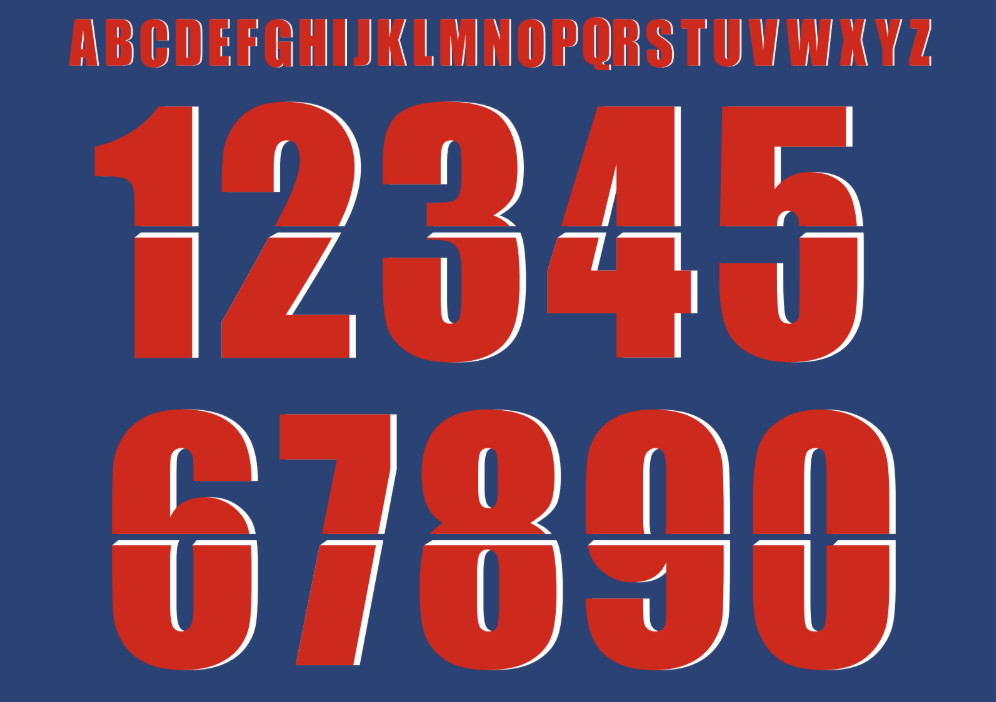
O Paris Saint-Germain nunca entra em campo apenas para jogar; o clube entra para desfilar estilo. Com a chegada do novo e expandido FIFA Club World Cup 2025, realizado nos Estados Unidos, a expectativa sobre os uniformes dos gigantes europeus é altíssima.
Neste post, trazemos para você a tipografia exclusiva que estampará as camisas de Marquinhos, Dembélé e companhia na busca pelo título mundial. Seja sob a assinatura da Nike ou da colaboração premium com a Jordan Brand, a fonte do PSG continua sendo referência em sportswear e moda.
Estilo Visual e Aplicação
A identidade visual do PSG transcende o futebol, e a fonte para o Mundial de 2025 reflete essa conexão com a cultura urbana e a alta moda. A tipografia apresenta traços arrojados e modernos, mantendo a legibilidade necessária para as transmissões globais, mas com detalhes angulares que remetem à arquitetura de Paris (como a Torre Eiffel) e à agressividade competitiva da Nike.
Esta fonte é versátil: ela funciona perfeitamente tanto nos kits “home” (azul tradicional) quanto nos uniformes “away” ou “third”, que costumam trazer a ousadia da Jordan. É a escolha certa para quem quer fugir do padrão genérico e aplicar uma estética de elite em seus projetos.
Dica de Designer: Para reproduzir fielmente o estilo dos jogadores, utilize o contorno (outline) interno ou sombra projetada, caso o kit específico da partida exija (comum em fontes de copas internacionais).